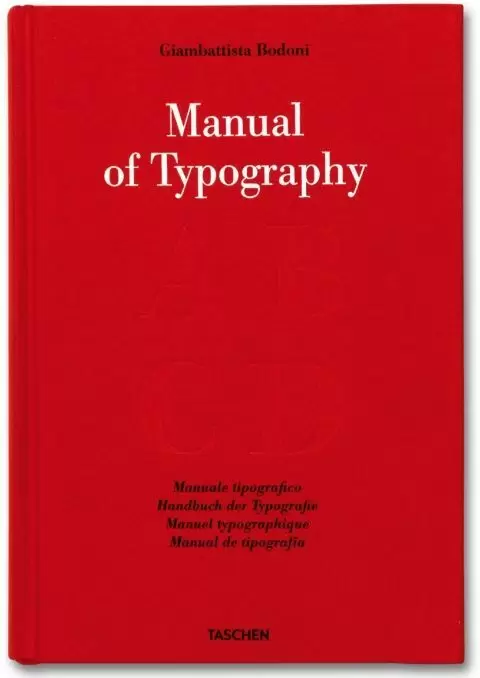
BODONI. MANUAL DE TIPOGRAFÍA ? MANUALE TIPOGRAFICO (1818)
Un celebrado impresor y diseñador tipográfico, Giambattista Bodoni estableció el estándar a la hora de imprimir el alfabeto, con su Manuale tipografico (1818). La edición en dos volúmenes —publicada póstumamente en una tirada limitada de 250 ejemplares— presenta 142 juegos de tipografías en redonda y cursiva, una amplia selección de filetes, ornamentos, símbolos y florituras, así como los alfabetos griego, hebreo, ruso, árabe, fenicio, armenio, copto y tibetano.
Impresor oficial del Duque de Parma, Bodoni (1740-1813) declaró que la belleza de la tipografía bien diseñada deriva de cuatro principios: la uniformidad del diseño, la nitidez y la elegancia, el buen gusto y el encanto. Sus tipografías exhiben un grado sin precedentes de refinamiento técnico y personifican la pureza y la gracia. La culminación de más cuatro décadas de trabajo, el Manuale tipografico representa uno de los mayores logros tipográficos de la historia. La tipografía Bodoni todavía se utiliza ampliamente incluso hoy, tanto en los medios digitales como en los impresos, y la meticulosa reimpresión de TASCHEN de la obra maestra de Bodoni brinda a los lectores una oportunidad excepcional de explorar sus orígenes y aprender sobre su creador.